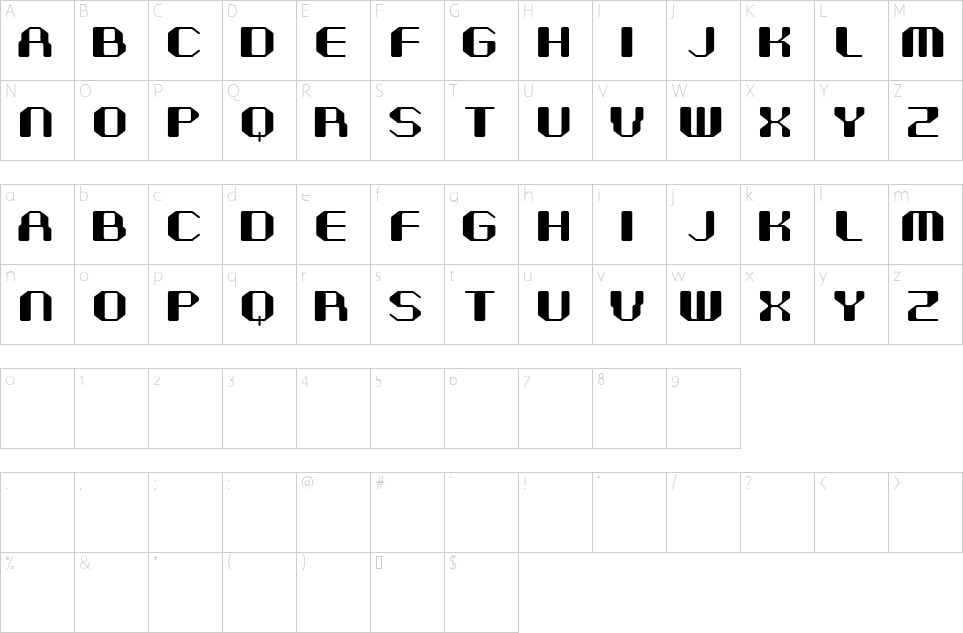
A Delaver é uma elegante fonte para Windows e Mac projetada por Vladimir Nikolic que se destaca pelo seu equilíbrio entre simplicidade e sofisticação. Inspirada nas formas geométricas modernas, a Delaver combina facilmente com diversos estilos de design, seja ele clássico ou contemporâneo. Seu design é ideal para uso em materiais digitais variados, como textos gráficos, logotipos e interfaces de usuário intuitivas. Sua simplicidade não apenas torna a fonte fácil de ler mas também permite que ela adorne qualquer projeto com delicadeza sem perder seu caráter único. Com design limpo e moderno, a Delaver é uma escolha ótima para quem busca um recurso gráfico versátil e elegante. Sua disponibilização gratuita é ainda mais incomum e valorizada, tornando-a uma opção perfeita para designers que buscam recursos de qualidade sem precisar recorrer a modelos de pagamento.